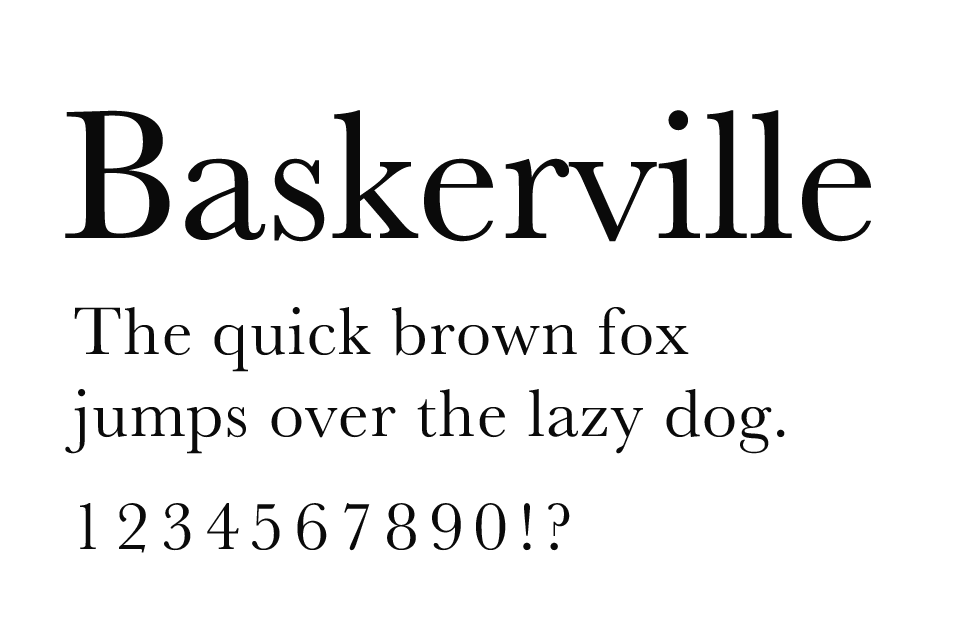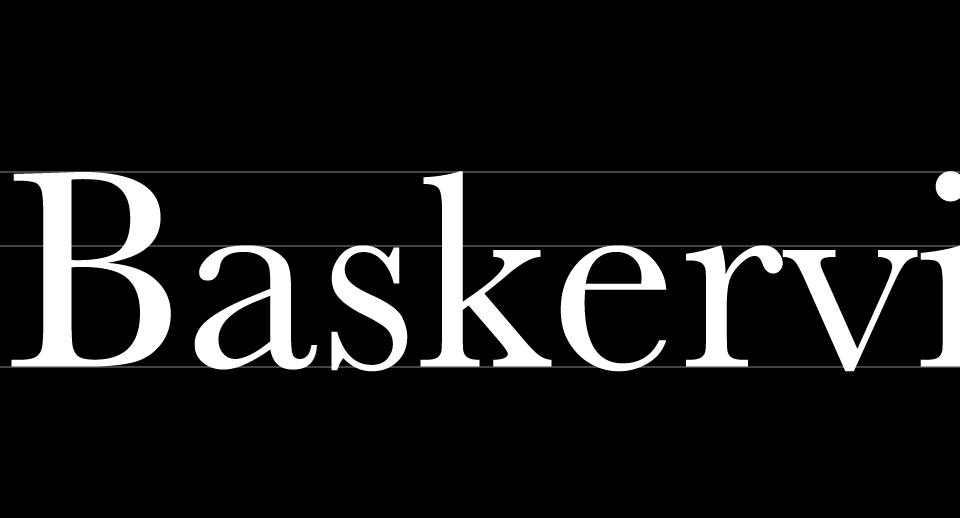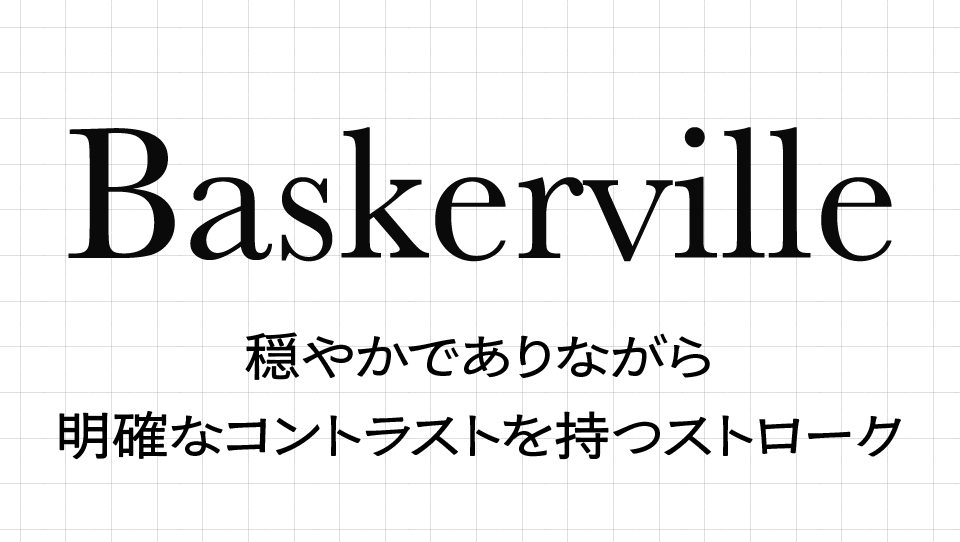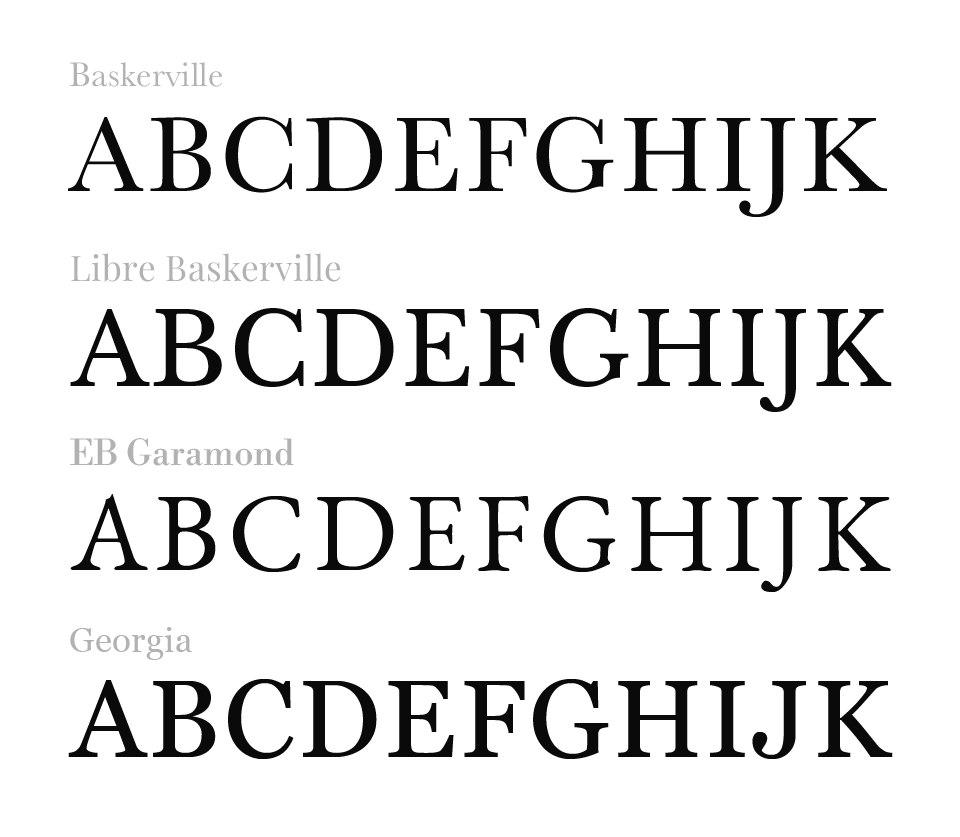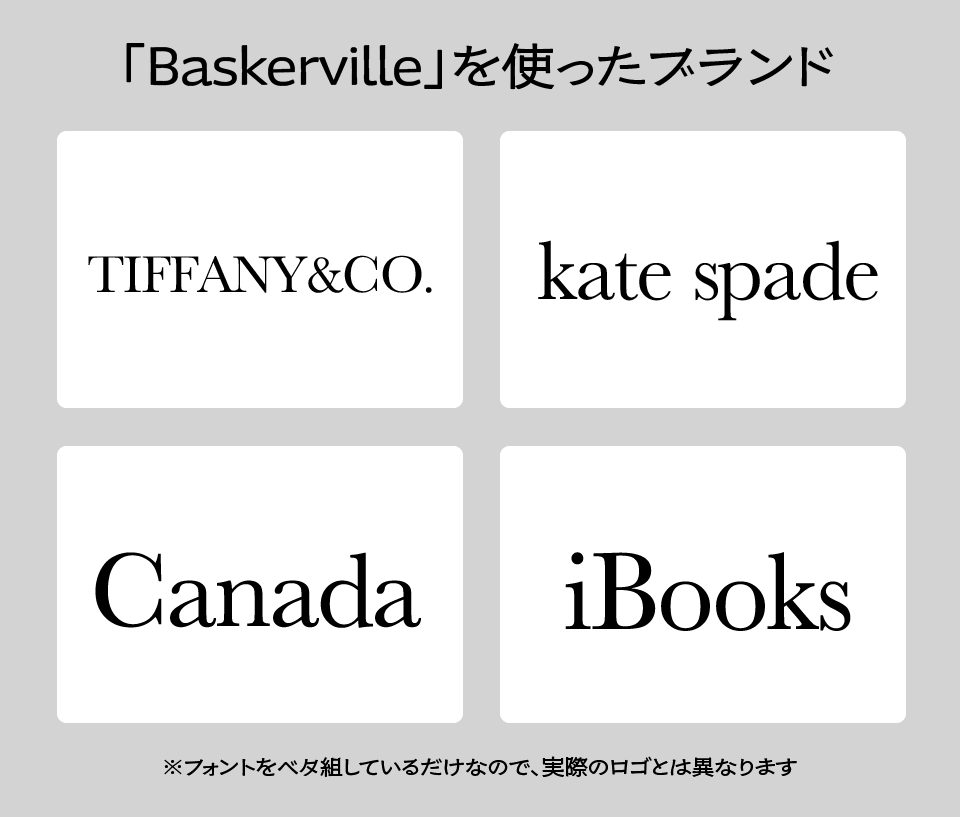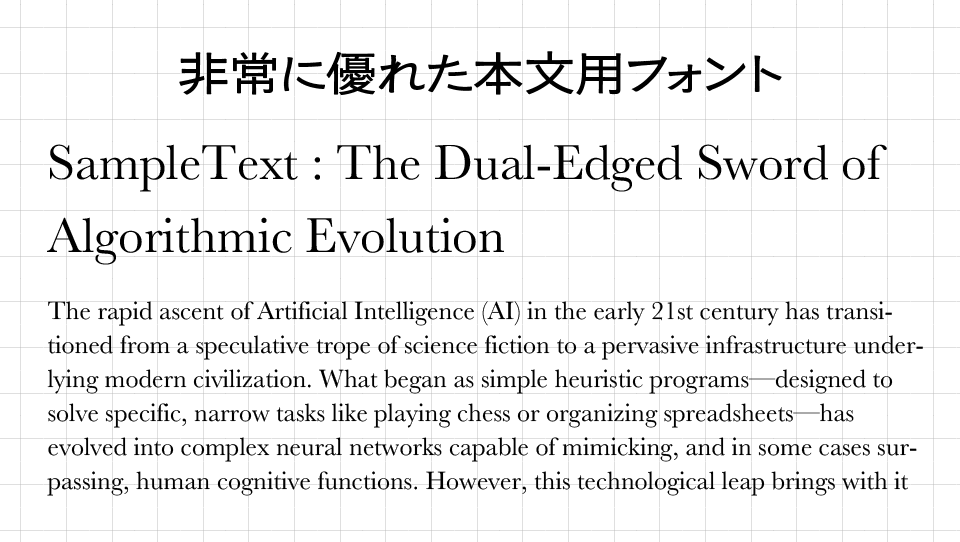
Baskerville(バスカヴィル)フォントの魅力とは?クラシックと理性を融合した上品で読みやすい書体
美しく読みやすく、静かな知性を感じさせる。そんなフォントを探しているなら「Baskerville(バスカヴィル)」という選択肢は外せません。18世紀に誕生したこのセリフ体フォントは、文学や学術の世界で長く愛されてきた歴史を持ち、現代でもタイポグラフィの基本として多くのデザイナーに選ばれています。
華やかすぎず、地味すぎず。理性的でありながら、どこか柔らかい気配をもつ——この記事では、Baskervilleの成り立ちと特徴、代替フォント、代表的な使用事例を交えながら、その奥深い魅力を掘り下げていきます。
Baskerville(バスカヴィル)とは
Baskervilleは、18世紀イギリスの印刷業者・書体デザイナーであるジョン・バスカヴィル(John Baskerville)によって1757年に制作されたセリフ体フォントです。彼は印刷技術そのものの改良にも取り組んでおり、従来よりも滑らかでコントラストのはっきりした書体を活かせる高品質な印刷を可能にしました。
その書体デザインもまた革新的で、オールドスタイル(Garamondなど)とモダンローマン(DidotやBodoni)の中間に位置するトランジショナル・セリフ体(移行期ローマン)として分類されています。これは、文字のストロークにある程度のコントラストを持たせながらも、自然で柔らかな印象を残すスタイルで、現代の可読性にも優れた設計になっています。
Baskervilleの歴史と背景
バスカヴィルが活動していた18世紀中頃のイギリスでは、印刷や出版文化が大きく発展しつつありました。そんな中で彼は、より高度な印刷品質と美しい書体を組み合わせることで、知的でエレガントな印刷物を生み出すことを目指しました。
彼のフォントは、従来のオールドローマン体よりも細部がシャープで、文字間の調和がとれており、当時としては先鋭的なデザインとされました。その美しさは一部で称賛される一方、保守的な印刷業界からは冷たい評価も受けたといいます。
しかしその後、フランスのディド家やイタリアのボドーニなど、後のモダンローマン体を生んだデザイナーたちに大きな影響を与え、Baskervilleはタイポグラフィ史における重要な“橋渡し”の書体となりました。
Baskervilleの特徴
Baskervilleのデザインは、穏やかでありながら明確なコントラストを持つストロークが特徴です。縦線と横線の太さには控えめながらも洗練された差があり、それが文字に自然なリズムと品格を与えています。セリフはやや細めで、先端がわずかに広がるようなフォルムを持ち、紙面上に柔らかなアクセントを加えます。
文字のxハイトは比較的低めで、アセンダーとディセンダーが長く取られているため、縦に流れるような優雅な雰囲気が漂います。また、全体的な字形のバランスが取れており、可読性が非常に高いため、長文の本文組みに最適です。過剰に装飾的ではなく、それでいて理性的な美しさを備えたフォント、それがBaskervilleの本質です。
類似・代替フォント
BaskervilleはAdobe FontsやMicrosoftの環境にも含まれていることが多く、比較的手に入りやすい書体です。しかし、より軽量な代替や無料フォントを求める場合、いくつかの優れた代替書体も存在します。
代表的なのがGoogle Fontsで提供されているLibre Baskerville(Google Fonts)。Web向けに最適化されており、印象や骨格はオリジナルに忠実です。また、EB Garamond(Google Fonts)もクラシカルで柔らかなセリフ体としてBaskervilleの雰囲気に近く、文学的なデザインとの相性も良好です。
さらに、有償書体ですが、TisaやGeorgiaなども読みやすく落ち着いた印象を持ち、Baskerville的な雰囲気を代替することができます。
Baskervilleが使われている代表的な事例
Baskervilleは、その知的で上品な印象から、文学作品・新聞・大学出版物・高級ブランドのエディトリアルなどでよく使用されています。
ロゴでは、Tiffany & Coやkate spadeなどは、目にした方も多いかと思います。
他には、欧米で発行されている書籍などに取り入れられていることが多く、Penguin Books(ペンギン・ブックス)の一部の文庫シリーズや、オックスフォード大学出版局(Oxford University Press)の書籍では、Baskervilleを基調とした文字組が多く採用されています。
また、AppleがiBooks(現Apple Books)の本文表示に一時期Baskervilleを採用していたこともあり、デジタルでも紙のような“読書体験”を表現するために用いられてきました。
ブランディングにおいても、クラシックと洗練の両方を求めるファッションブランドや高級ホテルなどがロゴや印刷物に取り入れることがあります。
Baskervilleを使うときの注意点
Baskervilleは非常に優れた本文用フォントですが、細いストロークや長めのディセンダーがあるため、小さすぎるサイズではつぶれて見えることもあります。特にデジタル環境では、解像度やアンチエイリアス処理の違いによって表示品質に差が出やすいため、紙媒体または高解像度デバイス向けの本文フォントとして使うのが理想です。
また、スタイリッシュで上品な反面、ポップさや勢いには欠けるため、エンタメ系やカジュアルな文脈ではやや場違いになることもあります。デザインのトーンとの相性を意識しながら使い分けることが重要です。
Baskervilleは、静かな知性を宿す“語り手”のようなフォント
Baskervilleは、控えめながらも芯のある、そんな人物を思わせるフォントです。大きな声では語らずとも、その佇まいに耳を傾けたくなるような、誠実で信頼感のある印象。だからこそ、学びの場や本の中で、長く読まれる言葉を支えてきたのかもしれません。